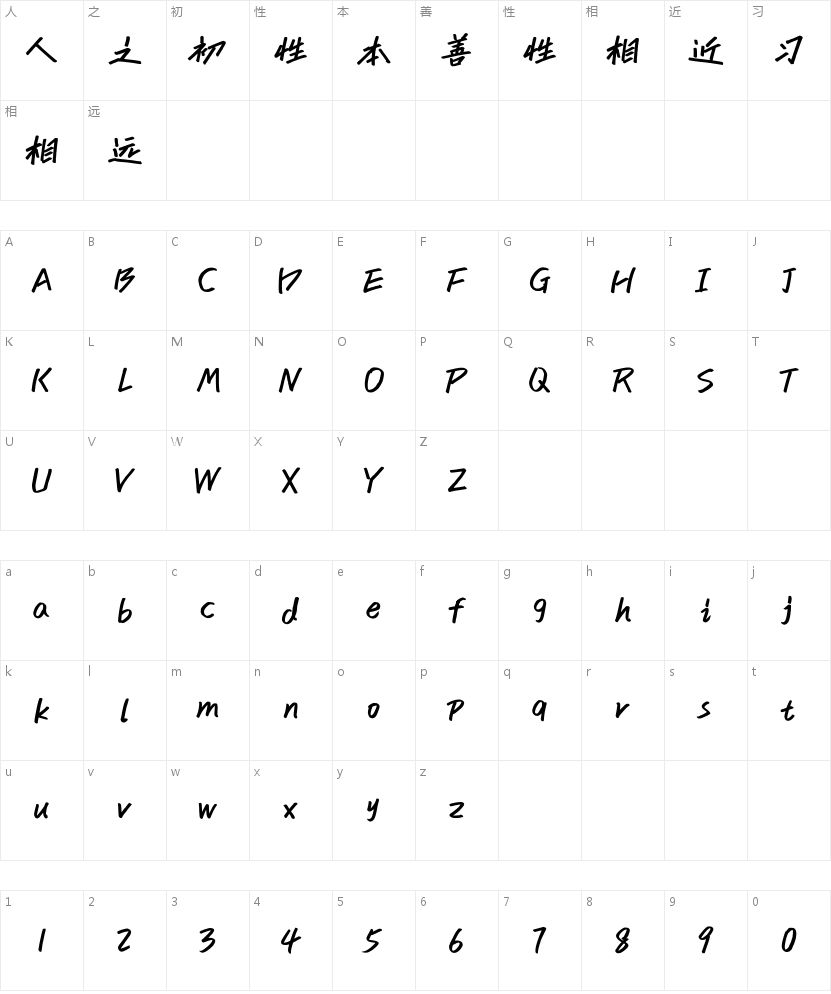
Aa追风手迹(Aa Zhui Feng Shou Ji)是一种优美的手写字体,以其流畅、自然和艺术性而受到广泛欢迎。 该字体的特点是笔画柔和,线条流畅,仿佛是一位熟练的书法家用毛笔潇洒地书写而成。它具有一定的笔画厚度变化,从而使每个字母都显得栩栩如生。此外,Aa追风手迹字体的字母间距离适当,使阅读更加舒适。 Aa追风手迹字体可用于书信、明信片、邀请函、海报、广告和其他文化创意设计中。它的自然和艺术性赋予了文本以独特的个性和魅力,使得文本更加引人注目并提高了视觉效果。文件名:AaZhuiFengShouJi-2.ttf
Aa追风手迹是一款非常不错的手写艺术字体,具有很好的视觉感,适合于文化类的宣传设计、商业类品牌的广告和产品包装设计以及个性化文字排版等较多场景。